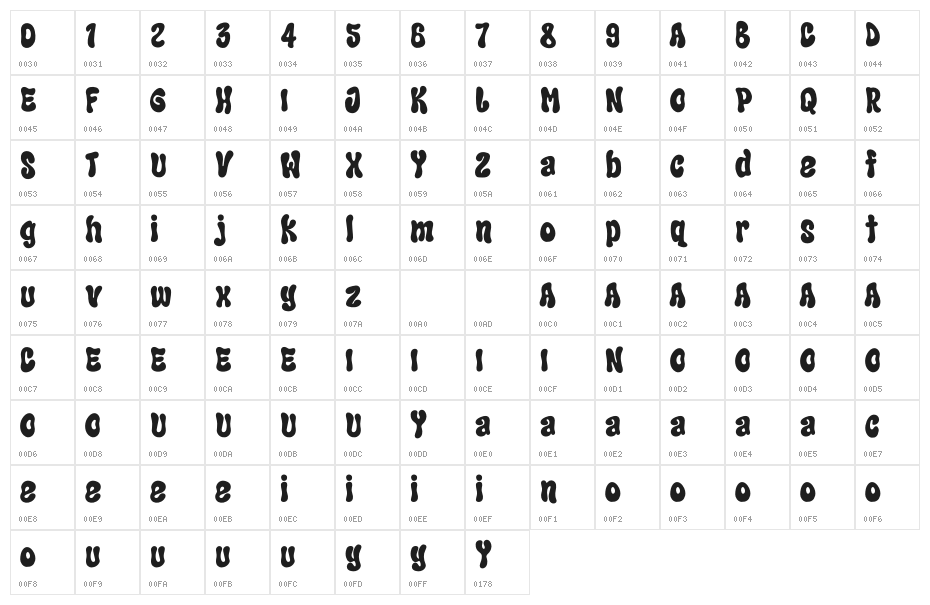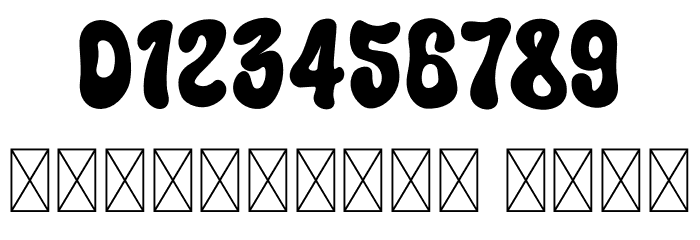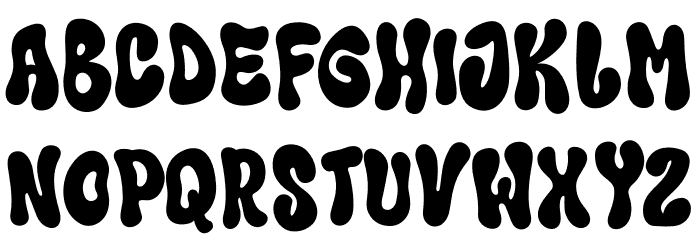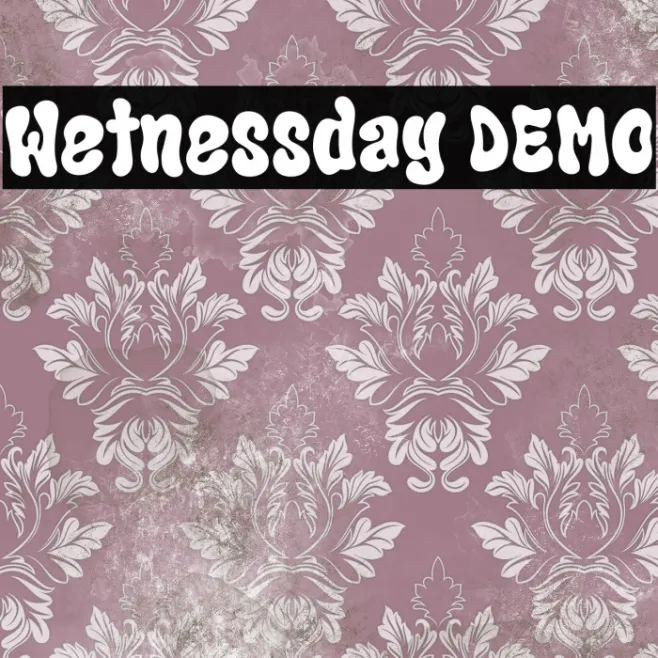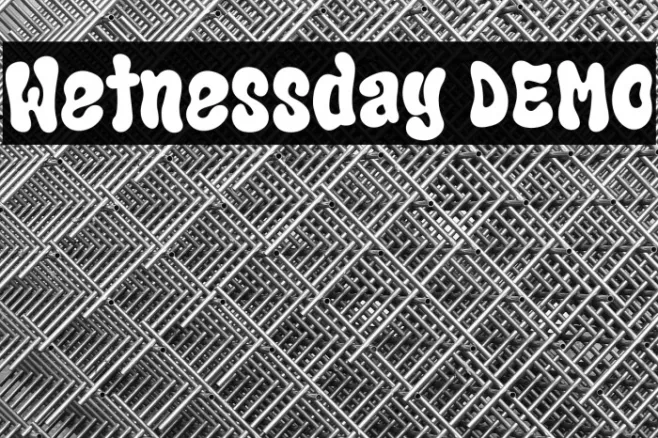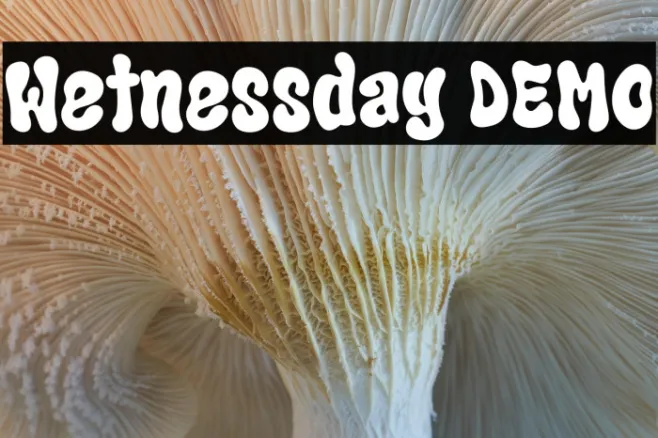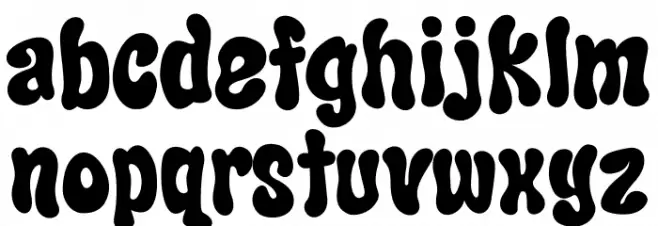
Wetnessday DEMO Font
| Gesamtstil | Playful, Whimsical |
| Vorgeschlagene Projekte | Ideal for children's books, playful branding, party invitations, and creative posters. |